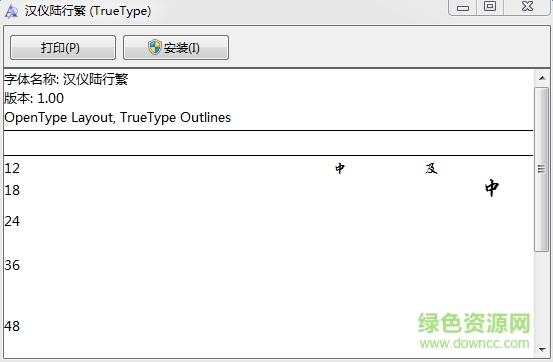
軟件介紹 軟件標簽: 漢儀字體 字體 漢儀陸行繁是一款很有特色的電腦繁體字,這種字體寫出來的字很好看,不拘一格,很適合書畫上面題字寫詩,當然還有很多方面都可以用到這款字體,有需要的朋友可以來綠色資源網(wǎng)下載。安裝說明:1.在綠色資源網(wǎng)下載字體包,并解壓縮2.最簡單的安裝方法:雙擊字體文件,點擊安裝按鈕即可2.批量安裝方法:將字體文件放到C:\Windows\Fonts溫馨提示:本站所有字體資源僅供個人學習與參考,如需商業(yè)使用請到相關(guān)官網(wǎng)授權(quán) 本字體如果商用,請聯(lián)系漢儀字體官方獲得授權(quán)。 軟件截圖 上一張下一張(1 / 1) 安裝詳細截圖 其他版本下載 標題 大小 更新日期 下載 下載地址 電腦版 漢儀陸行繁 點擊報錯 軟件無法下載或下載后無法使用,請點擊報錯,謝謝! 關(guān)閉報錯反饋 請描述您所遇到的錯誤,我們將盡快予以修正,謝謝! *必填項,請輸入內(nèi)容 本類最新 漢儀孟瑞體ttf v1.0 官方版 漢儀字庫免費 132款 阿里巴巴普惠字體 官方ttf版 漢儀字體打包大全 for Mac 蘋果電腦版_ 共131款字體 漢儀純愛情書拼音體 ttf版 漢儀北魏寫經(jīng)w字體 免費版 相關(guān)文章 Photoshop字體安裝使用方法和技巧 如何解決“無法新增字體”問題 Win 7系統(tǒng)安裝字體方法 網(wǎng)頁字體大小設置方法 怎么改網(wǎng)頁字體大小 在Linux系統(tǒng)中安裝字體的幾種方法 windows7字體顯示問題:打開某些程序的時候顯示的是亂碼 用戶評論 熱門評論 最新評論 發(fā)表評論 查看所有評論(0) 昵稱: 請不要評論無意義或臟話,我們所有評論會有人工審核. 字數(shù): 0/500 (您的評論需要經(jīng)過審核才能顯示)